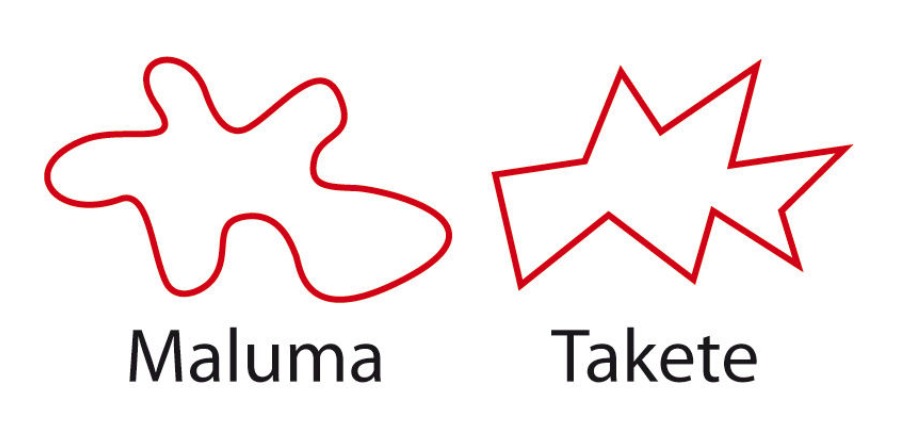
Typografie mit mehreren Schnitte, passend zum Wort "Maluma"
Hallo, ich suche eine Schrift mit (verspielten?) Rundungen, welche freundlich wirkt und zudem mehrere Schnitte (oder Fontpair-Empfehlung) hat.
Genauer geht es darum, ein längeres Zitat typografisch zu gestalten. Die Typo muss zum Wort "Maluma" passen. /https://www.maluma.de/Maluma.html)
Da es ein längeres Zitat ist (es gibt mehrere zur Auswahl), hätte ich gerne mehrere Schriftschnitte, um den Text interessanter zu gestalten. Es soll eine Art Poster werden. Rein mit Schrift. Bis jetzt finde ich leider nur einzelne Schriften mit maximal 2 Varianten.
Habt ihr mir vielleicht einen Tipp?
Hallo @holgi, die beiden Figuren, die du zeigst (oder ähnliche), sind in der Psycholinguistik als »Bouba« und »Kiki« bekannt. Wikipedia weiß näheres zum Bouba-/Kiki-Effekt.
Vermutlich in Anlehnung an die beiden Formen hat Hannes von Döhren 2020 seine gut ausgebaute und vor Rundungen strotzdende Bouba Round gestaltet oder zumindest getauft. Es wäre dann zwar ein »LTypI «, aber vielleicht ist das eine passende Schrift auch für dein Projekt.